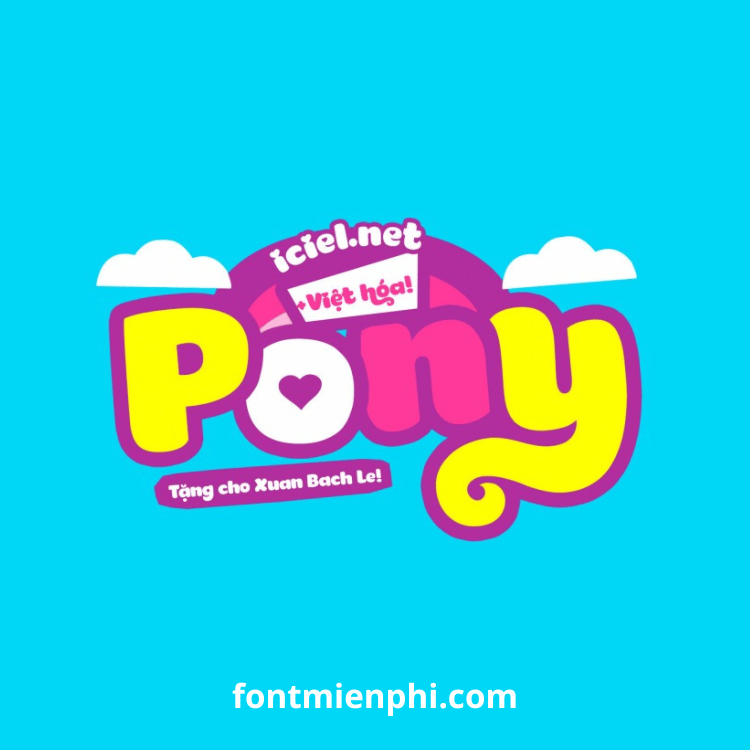
Việt hóa font iCiel Pony
Giới Thiệu Font iCiel Pony Việt Hóa
Font iCiel Pony Việt Hóa là phiên bản hoàn thiện với bộ ký tự tiếng Việt đầy đủ, dựa trên font chữ iCiel Pony gốc nổi tiếng với phong cách trẻ trung, đáng yêu. Đây là font chữ hoàn hảo cho các thiết kế hướng đến đối tượng trẻ em, giáo dục, truyện tranh hoặc các thương hiệu muốn tạo sự thân thiện, vui nhộn.
✅ Hỗ trợ đầy đủ bộ dấu tiếng Việt – Không lỗi font, hiển thị sắc nét
Đặc Điểm Nổi Bật Của Font iCiel Pony Việt Hóa
1. Phong Cách Thiết Kế Độc Đáo
• Nét chữ tròn trịa, mềm mại tạo cảm giác thân thiện, gần gũi
• Phù hợp cho các thiết kế hướng đến trẻ em, giáo dục, truyện tranh
2. Ứng Dụng Đa Dạng
• Thiết kế logo thương hiệu đồ chơi, trường học
• Làm tài liệu giáo dục, sách truyện thiếu nhi
• Thiết kế poster, banner sự kiện vui nhộn
3. Tối Ưu Cho Tiếng Việt
• Hỗ trợ đầy đủ bộ dấu tiếng Việt
• Cân bằng khoảng cách chữ chuẩn xác
Kết Luận